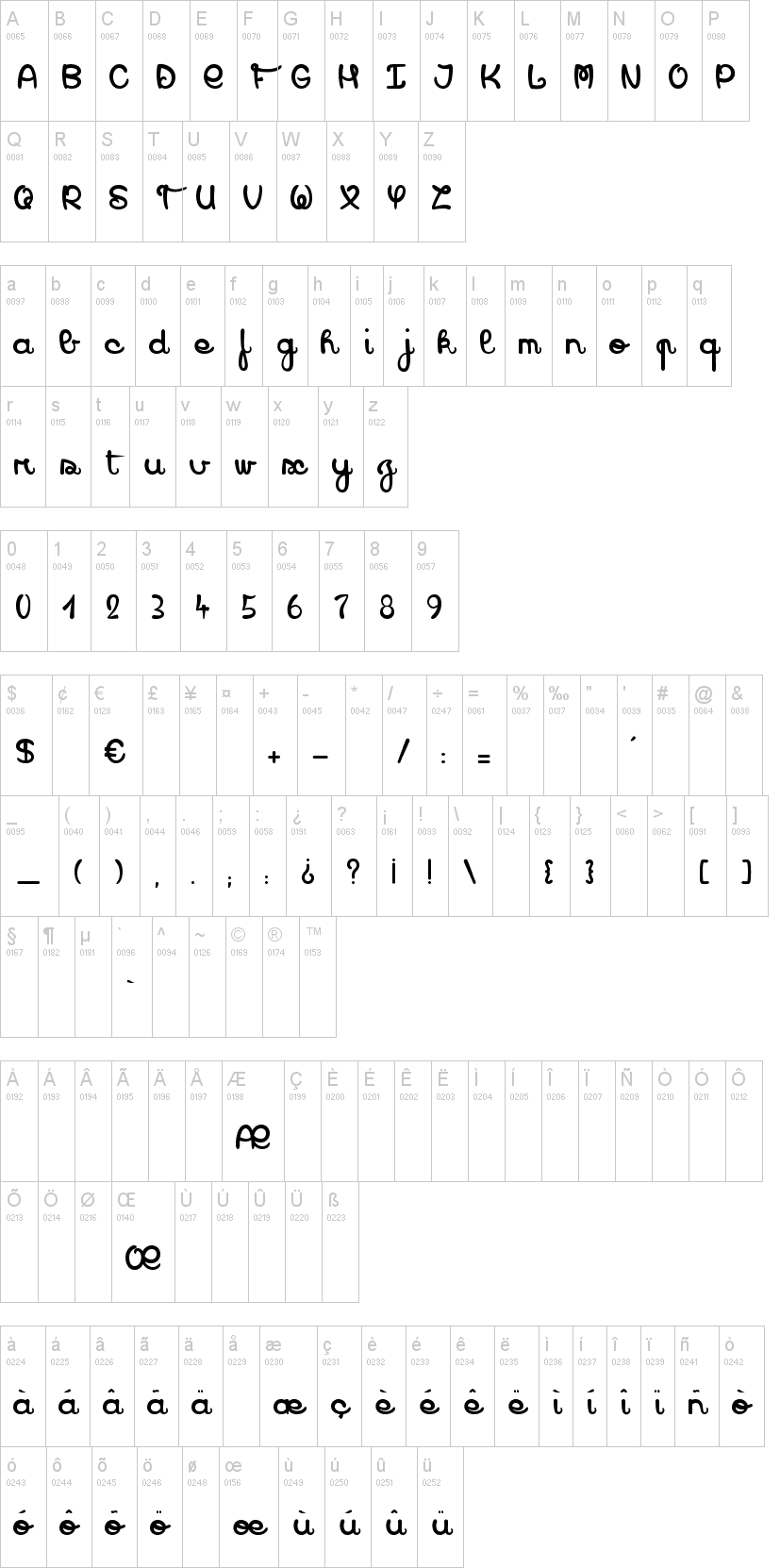
Sweet Dreamz
Sweet Dreamz是一种非常漂亮的手写风格字体。它的字形柔和、流畅,带有一些优美的装饰和弯曲的线条。这种字体非常适合用于设计卡片、海报、书籍封面等文化艺术领域的设计项目。另外,由于这种字体比较柔和,也可以用于设计一些轻松、温馨的品牌形象或标志。Sweet Dreamz字体是免费提供下载的,可以在许多字体网站上找到。
Sweet Dreamz是一款非常不错的手写艺术字体,具有很好的视觉感,适合于文化类的宣传设计、商业类品牌的广告和产品包装设计以及个性化文字排版等较多场景。
Sweet Dreamz字符映射图